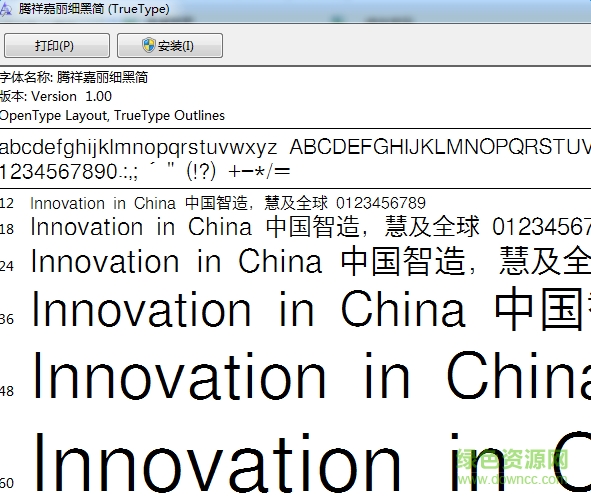
騰祥嘉麗細(xì)黑簡字體是一款超好用的個性中文字體,該字體非常正式,適用于多個設(shè)計領(lǐng)域,對于廣告的宣傳效果更是有了極強(qiáng)的襯托效果。需要的朋友趕快來綠色資源網(wǎng)下載使用吧!
騰祥嘉麗細(xì)黑簡字體是一款極具個性的字體,該字體十分飄逸,彰顯了自己的個性,有喜歡的朋友可以來綠色資源網(wǎng)下載使用!